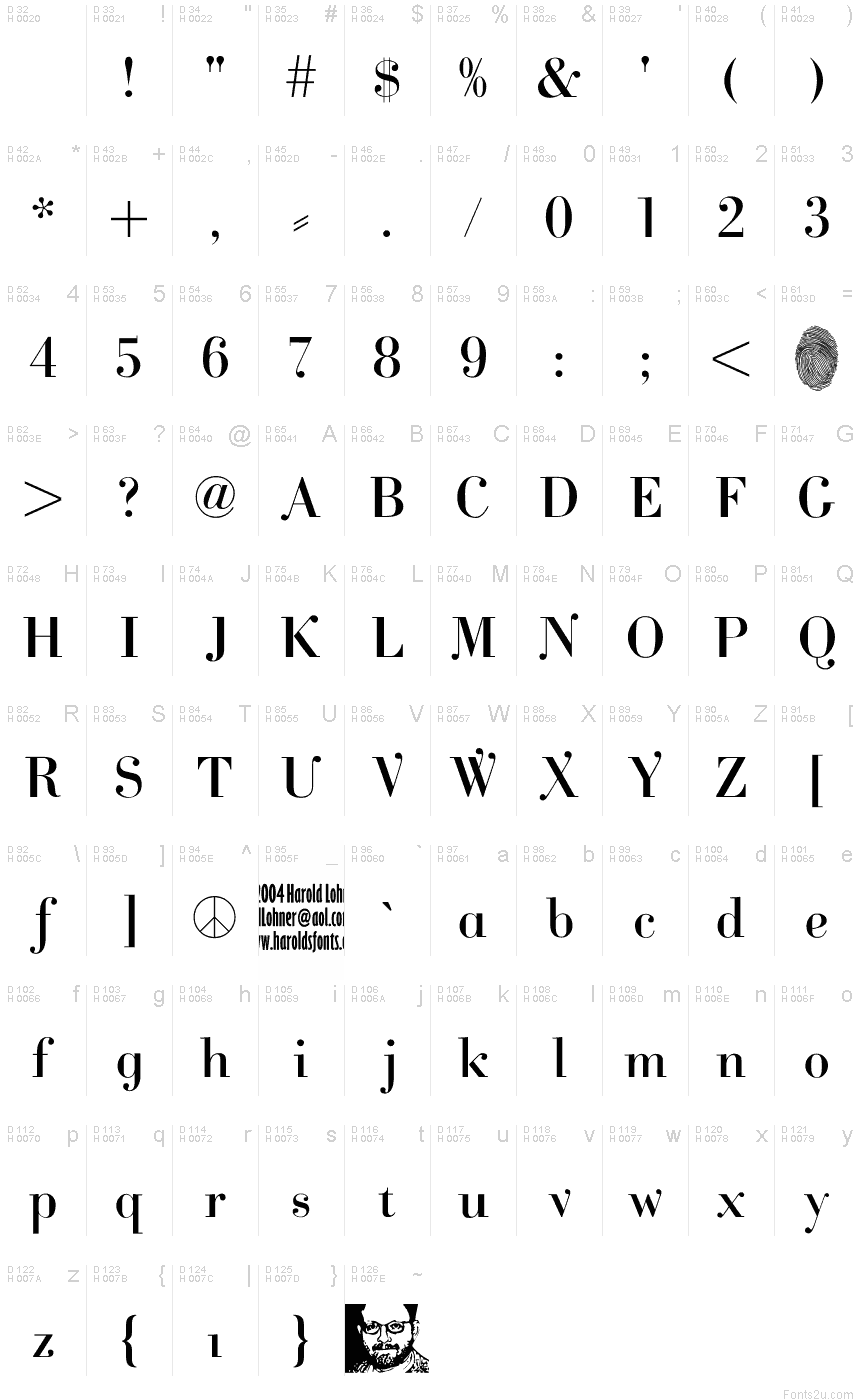
Cantabile
Cantabile od Harolda Lohnera to darmowy, wyrazisty krój szeryfowy. Zamaszyste krzywe, napięte piony i drobne, „atramentowe” detale nadają mu muzyczny rytm, który jest elegancki, ale nie sztywny, dzięki czemu nawet krótkie nagłówki prezentują się z klasą i zapadają w pamięć.
Cantabile świetnie sprawdza się na okładkach książek, w logotypach butików, zaproszeniach ślubnych, plakatach recitali, opakowaniach kosmetyków, menu kawiarni i tytułach redakcyjnych. Zestaw ten darmowy font ze spokojnym krojem bezszeryfowym w tekście głównym i daj mu nieco oddechu w większych rozmiarach, aby jego pełna wdzięku faktura mogła w pełni wybrzmieć.